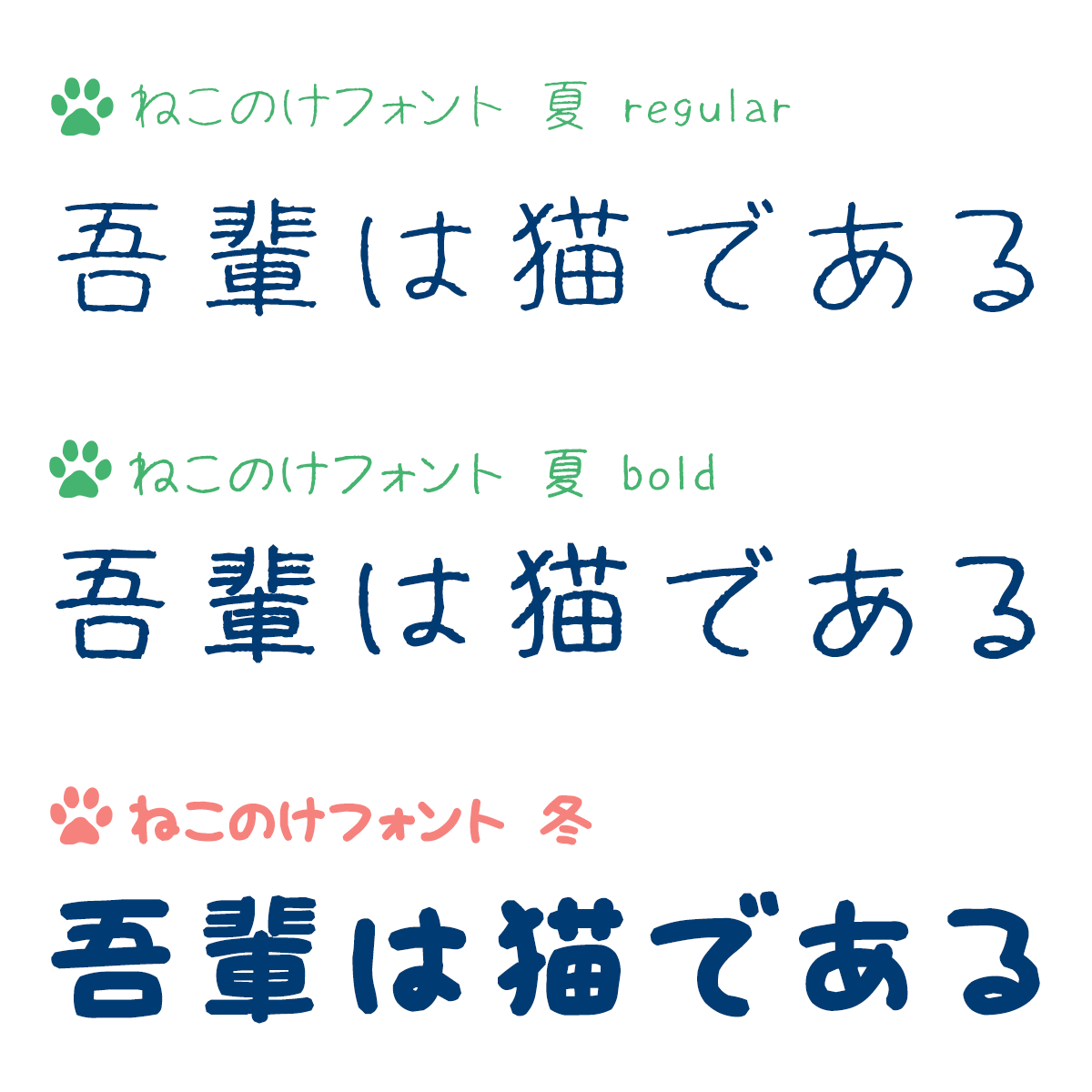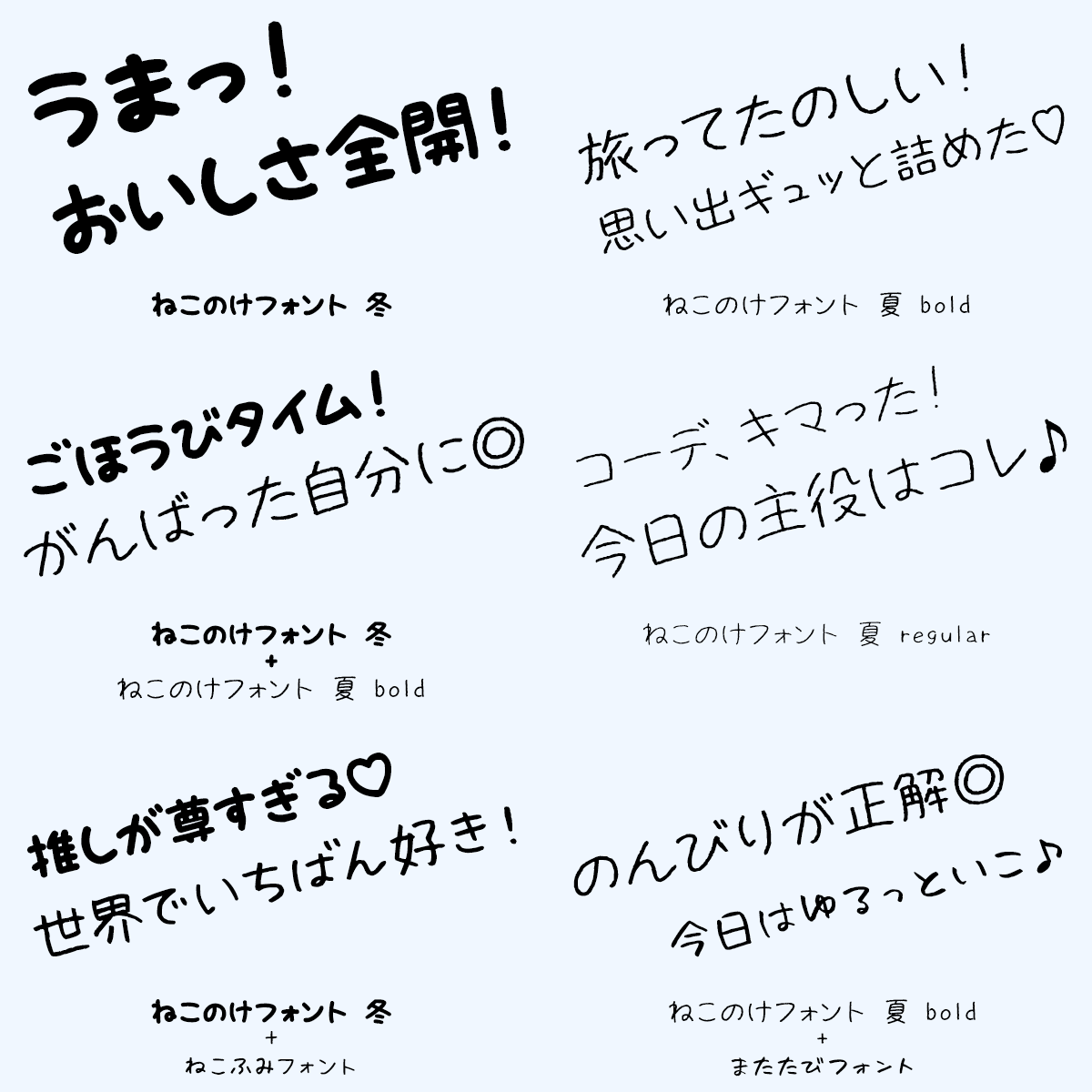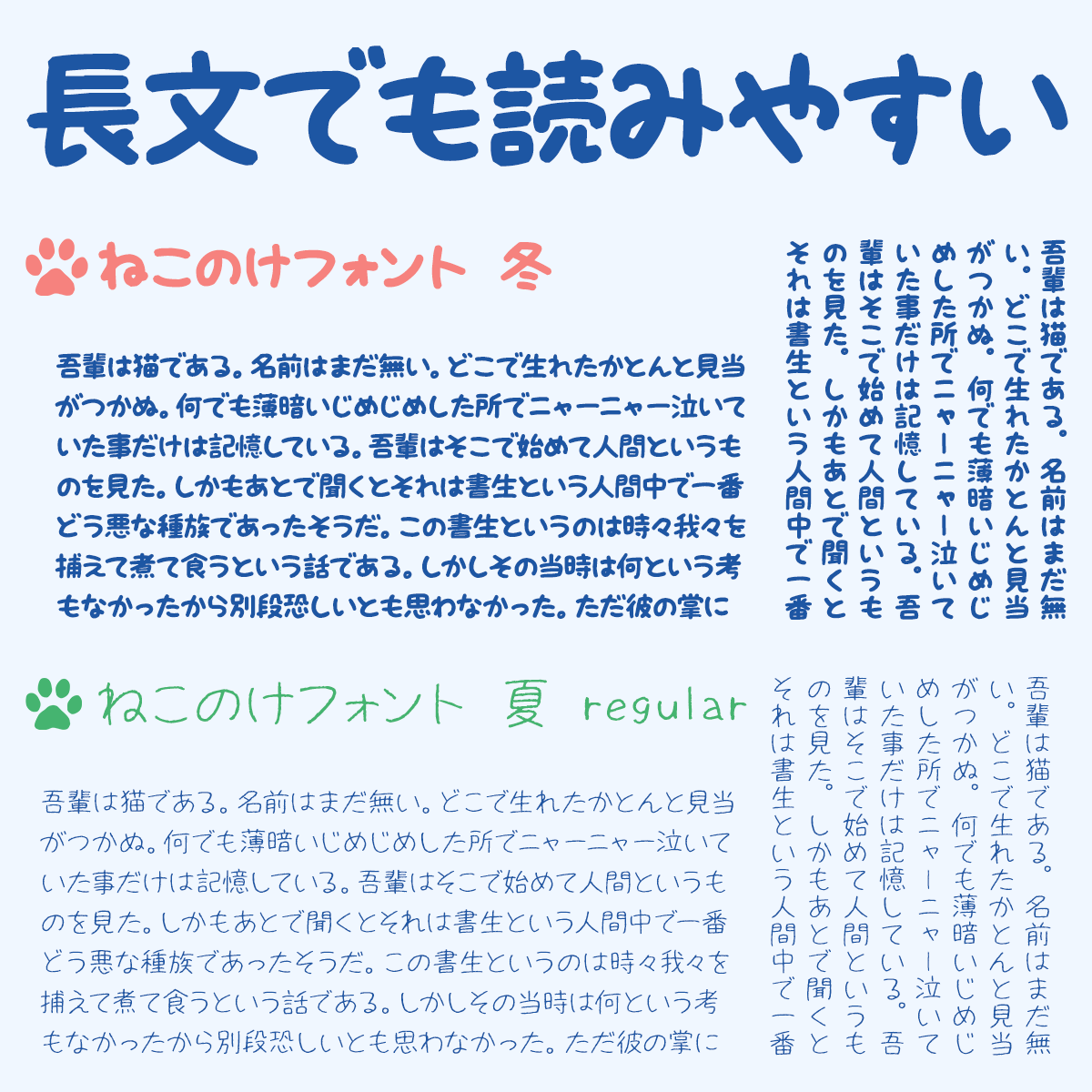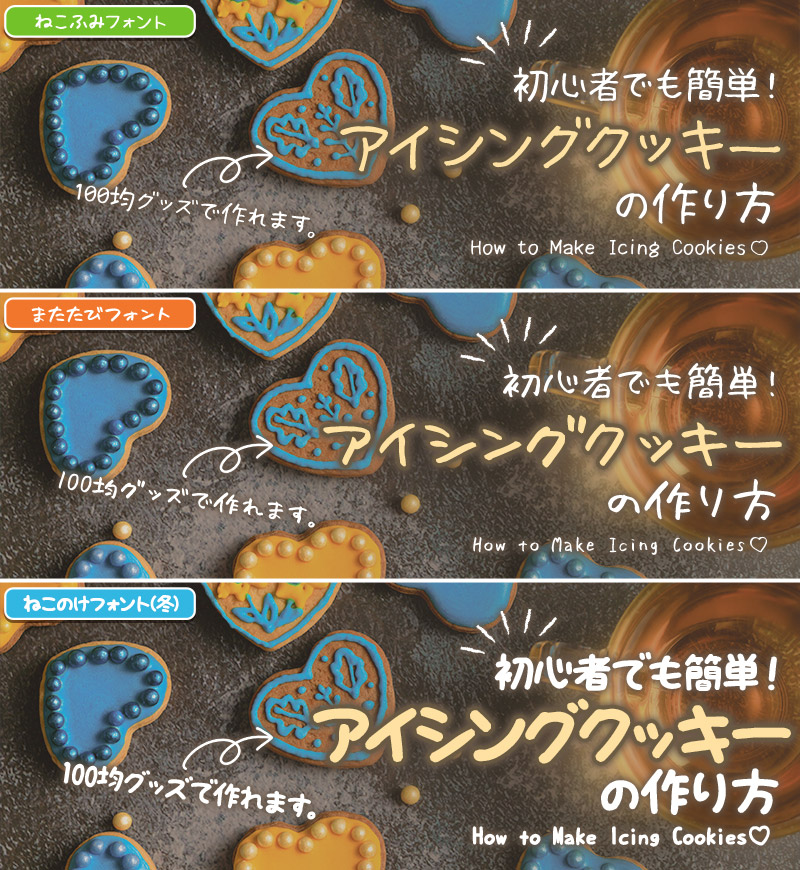
ゆるてがきこむ
『ゆるてがきこむ』では、ゆるくて可愛らしいデザインをたくさん取り扱っています。個性的で可愛い雑貨や動物のイラスト、リボンやフレームの飾り枠、吹き出しや矢印など、さまざまな素材とフォントを多数ご提供しています。
今回デザインポケットでご紹介する「ねこふみフォント」「またたびフォント」、そして最新作の「ねこのけフォント」は、柔らかいタッチとユニークなデザインが特徴で、猫好きの方にはたまらない手書き風のフォントです。
「ねこふみフォント」は、猫の足跡をイメージして、一文字ずつ丁寧に手書きされたフォントです。「またたびフォント」は「猫にまたたび、飼い主にはお酒」というテーマで、酔っ払ったときのユーモアあふれる文字を表現しています(実際に酔っ払いながら書かれたそうです)。
「ねこのけフォント」は、夏毛や冬毛が持つ印象をイメージして制作された手書き日本語フォントです。夏毛は細く軽やかなタッチで透明感のある雰囲気を、冬毛は太くやわらかなタッチで安心感やぬくもりを感じさせます。どちらも全て手描きで作られており、フォントの自然な揺らぎと人の手による温度感が魅力です。
3書体を組み合わせてみました
温かさや親しみやすさを与えるポスターやフライヤーに最適!
ねこふみフォント
日付・会場は、「ねこふみフォント」を利用しています。可愛らしいデザインと温かみのある手書き文字が特徴で、数字や英字も親しみやすいデザインになっています。
またたびフォント
「夜空をたのしむ、特別な夜。」は、「またたびフォント」を使用しています。個性的な手書き文字は、サイズが小さくても強いインパクトを持つため、視線を集めたい場面でも効果的です。
ねこのけフォント(夏)
「CAMP FESTIVAL」は、「ねこのけフォント(夏)」を使用しています。文字の縦横比がほぼ均等で、整った印象を与え、視認性が高く見やすいデザインに仕上がります。
相手に寄り添う手書きフォントで、個性と温かみを作品に注入しましょう。
ねこふみフォント
「手作り作品が大集結!」は、「ねこふみフォント」を利用しています。程よい太さでカジュアルな字形なので、見出しに使用するのに最適です。
またたびフォント
「ハンドメイド マーケット」や日付・会場は、「またたびフォント」を使用しています。作品のクオリティや魅力を一層引き立てる手助けになること間違いなしです!
ねこのけフォント(夏)
日付・会場は、「ねこのけフォント(夏)」を使用しています。文字の縦横比がほぼ均等で、整った印象を与え、視認性が高く見やすいデザインに仕上がります。
同じデザインで比較しました
可愛いイラストに手書きフォントを添えて
ねこふみフォント
イラストに合わせたカワイイ手書きフォントが、もっと魅力を引き出してくれます。
またたびフォント
筆サインペンで書かれた程よい太さのカジュアルなフォントに「またたびえもじ」を合わせると一段と可愛らしい仕上がりに!
ねこのけフォント(夏)
文字の大きさがしっかり揃っているので、他のシリーズよりも読みやすく、スッと目に入ってきます。
手作りの作品に手書きフォントを添えて
ねこふみフォント
親しみのある手書き文字は、手作り感あるデザインを演出します。
またたびフォント
癖のあるフォルムが作品の個性を際立たせます。
ねこのけフォント(冬)
ペンのカサカサした質感がリアルに再現されており、温かみと親しみやすさが一層引き立っています。
ねこふみフォントの特徴
猫たちに紙を踏まれながらも猫ファーストな優しい気持ちで書かれた、ゆるくてかわいい手書き文字です。
サインペンで書かれた程よい太さのカジュアルな字体。漢字に比べて仮名は少し小さくデザインされており、文字組みをすると文章にリズムが生まれるので可読性に優れていることも特徴です。
サインペンを使い猫ファーストで書かれたゆるかわ文字
文字組をすると文章にリズムが生まれるデザイン
般若心経もカバーする圧巻の収録文字
またたびフォントの特徴
お酒を飲みながら書かれた、よっぱらいのへろりとしたリアル系手書きフォントです。
筆サインペンで書かれた程よい太さのカジュアルな字体。漢字に比べて仮名は少し小さくデザインされており、文字組みをすると文章にリズムが生まれるので可読性に優れていることも特徴です。
ウェイト違い & 字形違いのフォント4点を同梱
本製品には「またたびフォント Regular」のほか、タイトル・見出しに適した太字ウェイト「またたびフォント Bold」、字形の酔いどれ具合が増したかなフォント「またたびぷらす」、さらにこれらと相性抜群の絵文字フォント「またたびえもじ」の4フォントが同梱されています。
1. またたびフォント Regular
酔いどれながら筆サインペンで書かれた、ゆるくてかわいい文字が特徴。
第二水準漢字まで収録の日本語フォントです。
2. またたびフォント Bold
またたびフォントの太字版。収録文字や字形はまたたびフォントRegularと同じです。
タイトルや見出しにどうぞ。
3. またたびぷらす
またたびフォントよりもひと回り大きく、より「へろっ」とした文字のかなフォント。
またたびフォントと組み合わせると抑揚が出ます。
▲ またたびフォントよりひと回り大きく、より「へろっ」とした字形
4. またたびえもじ
またたびフォントの文字と相性のよい絵文字フォントです。
文中で使いやすいデザインが83文字収録されています。
通常のひらがな部分に絵文字を収録
文字組をすると文章にリズムが生まれるデザイン
またたびフォント (Regular・Bold) のかな文字は、漢字よりも小さめに作られています。凸凹した高さの違いが文章にリズムを与えます。
またたびフォント Regular
またたびフォント Bold
かな部分に適宜またたびぷらすを混在させ、文章にさらなる抑揚をつけることもできます。
▲ オノマトペに「またたびぷらす」を使用してアクセントをつけた例
▲ 上段:すべて「またたびフォント」 下段:先頭と末尾に「またたびぷらす」使用
般若心経もカバーする圧巻の収録文字
(またたびフォント Regular・Bold)
※本サンプルは「またたびフォント Regular」で作成
ねこのけフォントの特徴
手描きのリアル感
ねこのけフォント 夏 冬 手書きフォント 手描きのリアル感
すべての文字を一つひとつ手描きで制作。自然な揺らぎや人の温もりがあり、デジタルながらも親しみやすい印象を与えます。
夏毛と冬毛をイメージした2種類のタッチ
ねこのけフォント 夏 冬 手書きフォント 夏毛と冬毛をイメージした2種類のタッチ
夏毛(細字):さらりと軽やかで、すっきりとした印象
冬毛(太字):ふっくらとして、やわらかくあたたかみのある印象
質感を再現したのではなく、それぞれの「ような印象」を文字で表現しています。
用途やシーンに合わせて選べる・組み合わせられる
ねこのけフォント 夏 冬 手書きフォント 用途やシーンに合わせて選べる・組み合わせられる
細字の軽やかさ、太字の存在感。単独で使っても良し、両方を揃えて印象を切り替えて使っても自然に調和します。
バランスの取れた漢字&かな文字
ねこのけフォント 夏 冬 手書きフォント バランスの取れた漢字&かな文字
漢字とひらがな・カタカナの大きさに極端な差のない程よいバランス。横書きだけでなく縦書きでも整ったレイアウトを作りやすくなっています。
豊富な文字収録
ねこのけフォント 夏 冬 手書きフォント 豊富な文字収録
ひらがな・カタカナ・漢字・英数字・記号など、幅広くカバー。文章にもタイトルにも対応可能です。
『ゆるてがきこむ』とは?
ねこふみフォントの生みの親 ねこふみゆちこさんについて